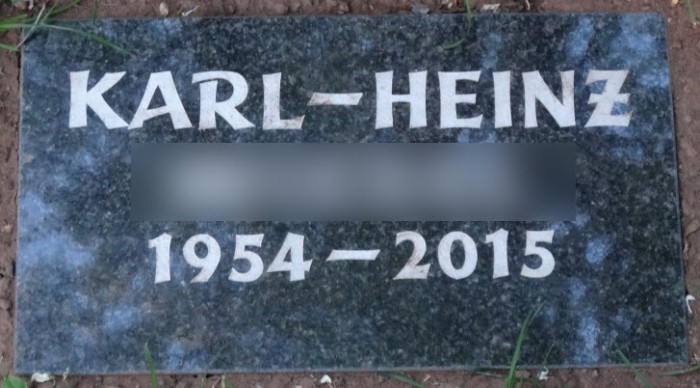
Schriftart von Grabstein gesucht
auf meiner Suche nach der Schriftart auf dem folgenden Bild bin ich auf dieses Forum gestoßen. Hier kann man mir bestimmt helfen.
Um der Stadtverwaltung klar zu machen was wir uns wünschen, würde ich gerne deren Standardschriftart übernehmen sodass ich damit die Anordnung nachstellen kann.
Das R und Z sind denke ich schon recht markant. Ich könnte mir vorstellen dass es keine allzu seltene Schriftart ist, aber in meinem Portfolio habe ich sie leider nicht gefunden.
Könnt ihr mir helfen? Wenn ihr eine Annäherung an diese Schriftart kennt wäre mir damit auch schon sehr geholfen.
Schriftarten für Grabsteine sind ja oft keine Computersatzschriften, sondern eben eigens für diesen Zweck gemachte, die man sich aus dem Katalog des Steinmetzes aussuchen kann.
Ich denke daher eher nicht, dass du genau diese Schriftart als Font finden wirst, aber es gibt sicher jede Menge ähnliche, z.B. die Optima Bold.
Wenn du den Steinmetz ausfindig machen kannst, kannst du bestimmt auch den fragen, welche Schrift er benutzt hat.
Da der abgebildete Grabstein ja noch recht neu ist, würde ich einfach mal die Steinmetze der Umngebung abklappern, mit dem Bild.
Gerade in dem Gewerbe haben die gern das irgendwann von einem ihrer Schreibmeister gestaltete Schriftenalbum quasi als Betriebs-Handschrift. Das hatten wir hier öfter.
Und manchmal schafft es so eine Schrift dann tatsächlich in den Schatz der Satzschriften - man denke noch an H. Zapfs 100 Lire Schein.